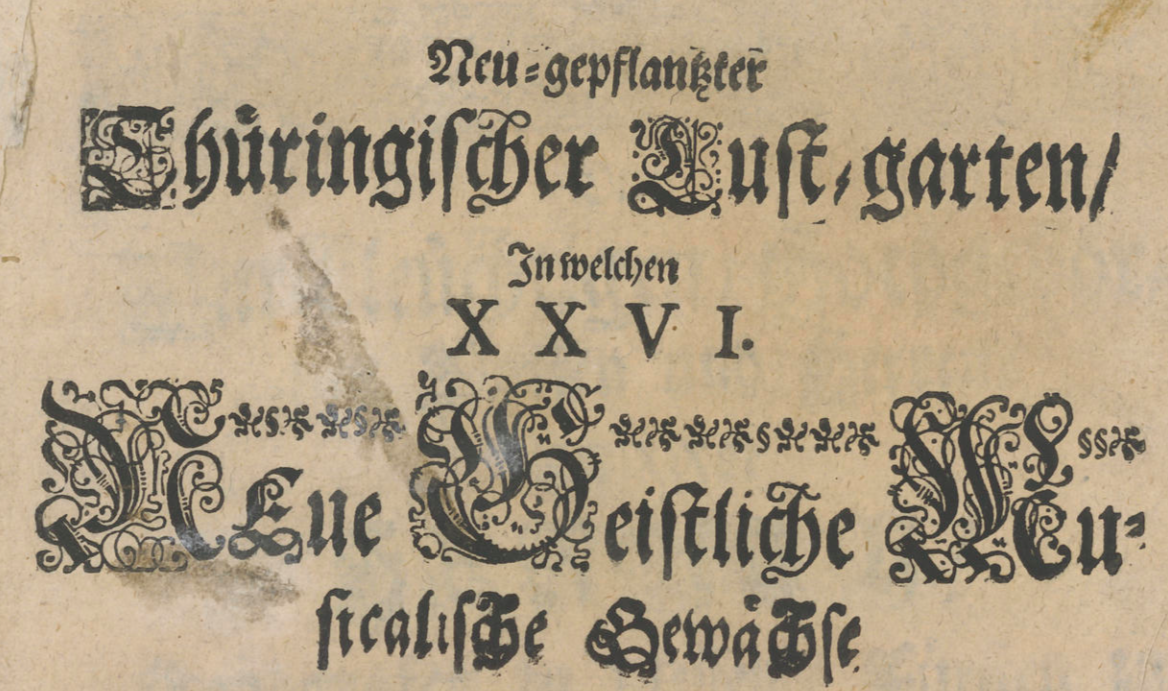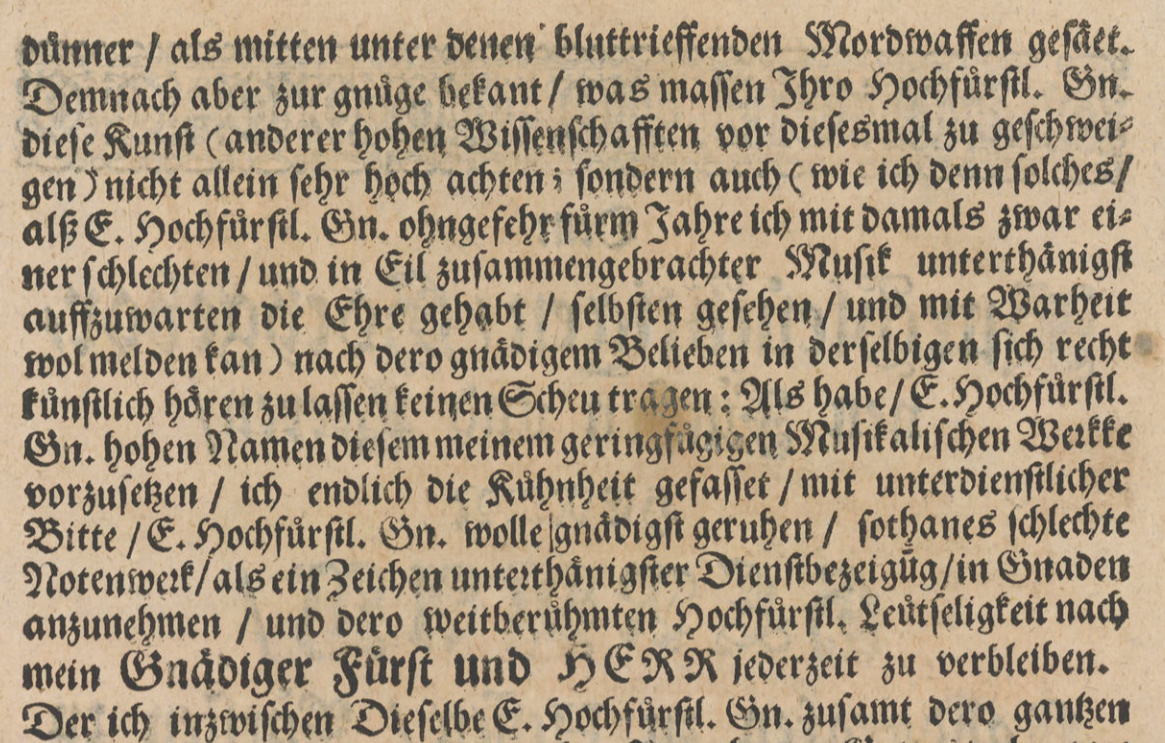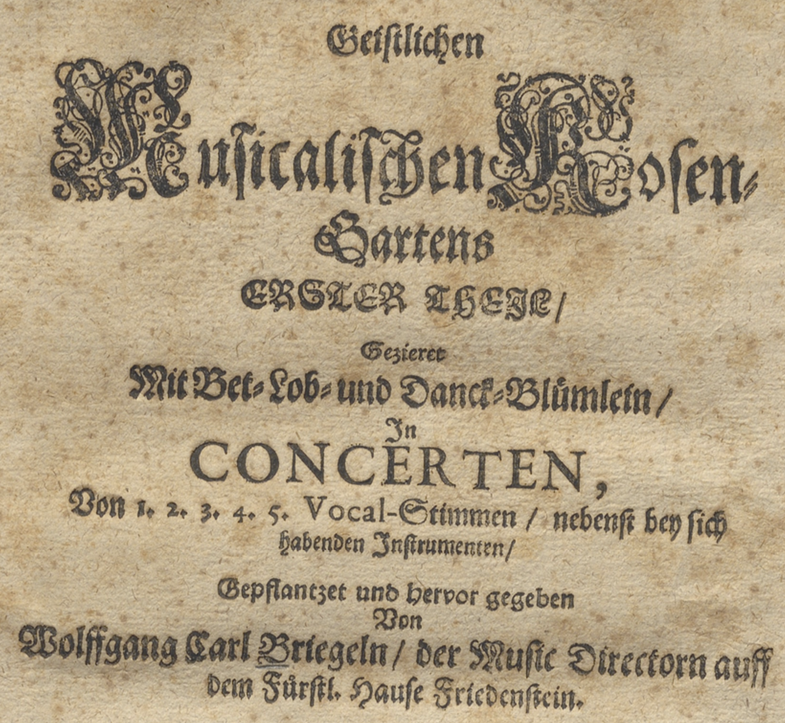
Suche Frakturschrift des 17. Jahrhunderts aus Deutschland
im Rahmen eines von mir durchgeführten Editionsprojektes mit Musik des 17. Jahrhunderts möchte mein Auftraggeber die Titelseite der herauszugebenden Publikation dem Original entsprechend möglichst ähnlich abgebildet haben. Sie soll aber „nachgesetzt“ werden – ein Foto scheidet also aus. Zu diesem Zweck benötige ich eine digitale Frakturschrift, die der auf den angehängten Bildern möglichst ähnlich ist. Hat da jemand eine zündende Idee? Wichtig wäre vor allem, dass der Font die Umlaute mit kleinem e über den betreffenden Buchstaben enthält.
Weitere Informationen zu den Abbildungen:
Es handelt sich um zwei Musikdrucke aus der Mitte des 17. Jahrhunderts, die in Thüringen hergestellt wurden. Die Drucker sind Johann Hüter (Mühlhausen 1657) bzw. Johann Michael Schall (Gotha 1658).
Ich habe vor einiger Zeit mal nach Frakturschriften gesucht, um das Titelblatt eines Musiktheoriebuches aus der Mitte des 18. Jahrhunderts "nachzubauen". Ich bin nicht wirklich fündig geworden. Ich habe mich, wenn ich mich recht erinnere, mit einem Font begnügt, der als Chursächsische Fraktur verfügbar ist (war stilistisch auch nicht voll befriedigend, aber vor allem war die Qualität des Fonts unzureichend). Und ich habe einen Blick auf die Leibniz Fraktur geworfen (gute Qualität, stilistisch aber noch weiter entfernt). Ich fürchte, für die Mitte des 17. Jahrhunderts sieht es noch schlechter aus. Alle Frakturkataloge, die mir spontan einfallen, basieren zumeist auf Quellen und Interpretationen des 19. Jahrhunderts.
In meiner Erinnerung war das Hauptproblem die Kombination aus recht schlichter Gestaltung und schmaler Laufweite der Buchstaben. Alles, was ich damals gefunden habe, wirkte stilistisch zu "modern". Und 100 Jahre früher sieht es, wie gesagt, wahrscheinlich noch dünner aus. (Die besonderen Umlaute sind dabei noch das geringste Übel; die könnte man im Zweifel einfach selbst bauen und dann ersetzen.)
genau das ist auch meine Beobachtung. Es gibt einige wenige Fonts, die Frakturschriften des 17. und 18. Jahrhunderts nachempfunden sind. Diese kann man bei Peter Wiegel oder Dieter Steffmann sogar gratis finden. Vergleiche mit originalen Drucken der damaligen Zeit zeigen dann aber meist doch erhebliche Unterschiede bzw. Modernisierungen. Und die vereinzelten Fonts, die tatsächlich versuchen, barocke Schriften akkurater abzubilden, sind oft handwerklich nicht gut gemacht. Für den Moment bin ich bei der DS-Wartburg-Fraktur von Delbanco gelandet. Die ist zwar nicht vollkommen zufriedenstellend, liefert jedoch ein Ergebnis, mit dem ich leben könnte.
Vielen Dank dafür. Dieses Schriften-Paket besitze ich bereits seit sehr vielen Jahren (so wie viele andere Schriften von Walden Font). Und so sehr ich die Arbeit dieses Herstellers auch schätze, muss ich doch sagen, dass ich die ausgefransten Konturen der von mir favorisierten Frakturschriften nicht so schön finde. Allerdings finde ich auch keine Schrift des Gutenberg-Paketes so richtig passend für meine Zwecke.
Diese Schrift ist geschrieben - keine Druckschrift. Du siehst das an den Abweichungen gleicher Buchstaben. Wie gefällt dir die Walbaum Fraktur? Kommt doch einigermaßen gut ran! Die Umlaute müsste man selbst erstellen/austauschen - z. B. mit FontForge.
Für die Schuckbuchstaben habe ich aus etwas gefunden: UechiPlain.